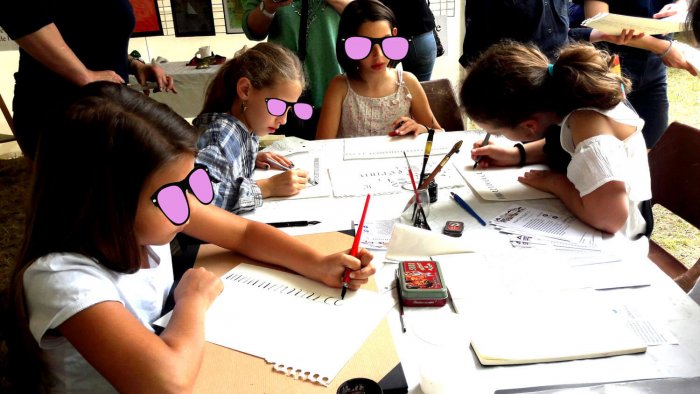
J’avais promis de revenir avec de la calligraphie dans mon dernier article  ! Je reviens d’une après-midi complète rythmée par l’encre et les plumes, dans le cadre de la journée de la Créativité, qui a eu lieu à Verneuil-sur-Seine (78). Cette journée est hébergée par l’association Tamaris de Verneuil donc, et organisée par la talentueuse artiste Bénédicte Charpentier, qui donne des cours de dessin, de peinture et de sculpture à ses élèves adultes comme enfants. Ce dimanche, les élèves ont exposé leurs créations de l’année dans le parc de l’Orangerie, l’occasion de découvrir de magnifiques tableaux, pastels et modelages dans un cadre bucolique et une ambiance très familiale.
Les œuvres exposées par les élèves.
Mon fils aîné suit les cours de Bénédicte depuis deux ans et exposait à cette occasion. J’avais proposé de venir faire une petite animation sans chichi autour de la calligraphie, en mode démonstration décontractée, pour faire découvrir cet art si peu connu. Me voici donc partie avec quelques feuilles, des plumes variées pour expliquer les différents outils du calligraphe, et de l’encre. Très vite, un jeune garçon a voulu essayer et a rejoint ma table. Il a été un peu difficile de bien le guider, car il est gaucher (!), mais il a vite pris plaisir à tracer ses premiers traits et ses premières lettres.
L. découvre les plaisir de l’écriture à la plume
Je vous laisse deviner la suite… Allez, en images :
Le premier groupe de groupies (les jolies lunettes sont là pour préserver leur vie privée…)
Second groupe : les calligraphes en herbe écoutent les instructions avec attention
Voilà comment une simple démo a tourné en atelier improvisé !
Pour démarrer, les enfants ont tracé 3 traits de base :
• Le trait vertical, descendant
• Un croissant ouvert comme le C
• Le même croissant inversé
Avec ces trois gestes, nous avons pu commencer à former des lettres en « Fondamentale » : a, d, l, i…. Puis des mots – enfin, leurs prénoms afin que chacun puisse repartir avec sa feuille et son nom calligraphié.
J’ai été touchée par la motivation et l’intérêt suscité par la calligraphie auprès des enfants. J’ai surtout été bluffée par leur sérieux, leur concentration, leur volonté de bien accomplir les gestes. Ce n’était pas évident d’improviser sur un temps si court et d’aller à l’essentiel, et pourtant cela a été possible et franchement sympathique.
J’ai eu aussi une élève extrêmement motivée, qui me disait que son écriture à l’école était catastrophique, mais qui voulait bien essayer. Prise au jeu, elle est revenue en fin d’après midi, et en parallèle du petit groupe de débutants, elle s’est installée, a pris mon ductus  de Fondamentale, et toute seule a rempli sa page  avec l’alphabet entier « pour pouvoir le recopier chez moi » ! J’ai vraiment été touchée par cette jeune fille d’une dizaine d’année, par sa volonté, et… par la qualité de ses traits ! Et oui, elle avait un geste d’une justesse incroyable, elle qui « écrit si mal à l’école ». J’avais peut-être sous les yeux une future grande calligraphe, l’avenir le dira.
Découverte de la Calligraphie par P., sous mon regard médusé !
Conclusion
J’étais partie dans l’idée de faire des lignes et de présenter différentes écritures avec différents instruments… L’après-midi a pris une toute autre tournure, et je dois dire que j’ai passé un moment génial. Je remercie d’ailleurs tous les calligraphes en herbe, pour leur sérieux, leur fraîcheur, leur bonne humeur. Je m’excuse auprès des parents pour les doigts plein d’encre, mais c’est le métier qui rentre !
J’ai été très heureuse de l’engouement général autour de l’activité. Les enfants sont frais, n’ont pas peur, n’ont pas de préjugés et se lancent. Même si la calligraphie est un art difficile, répéter le geste jusqu’à ce qu’il soit juste n’est pas un problème : c’est comme un jeu même si cela demande de l’application. Une lettre est réussie, hop on gagne le fait de passer à la suivante !
Cela m’a motivée pour organiser d’autres moments de découverte, et je vais sérieusement y réfléchir pour la rentrée.
En attendant, je vous livre pour finir quelques mantras que mon amie Bénédicte instille à ses élèves afin qu’il expriment pleinement leur potentiel. Je les trouve très justes, pleins de sagesse et inspirants pour tous ceux qui n’osent pas, alors tout en est eux et que nous sommes tous des artistes en puissance :
Et enfin un dernier : « Travailler avec le temps révèle l’inconnu »